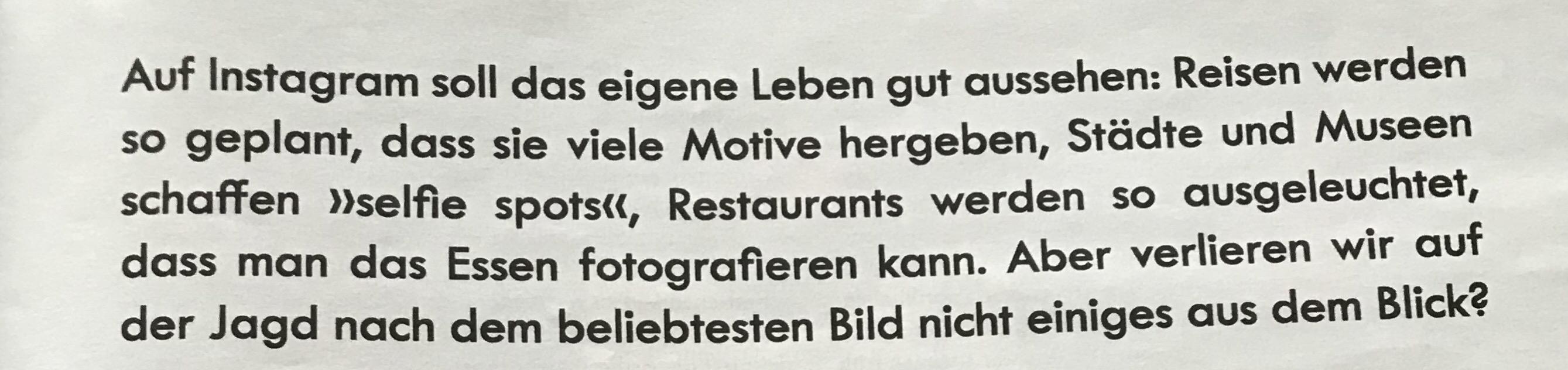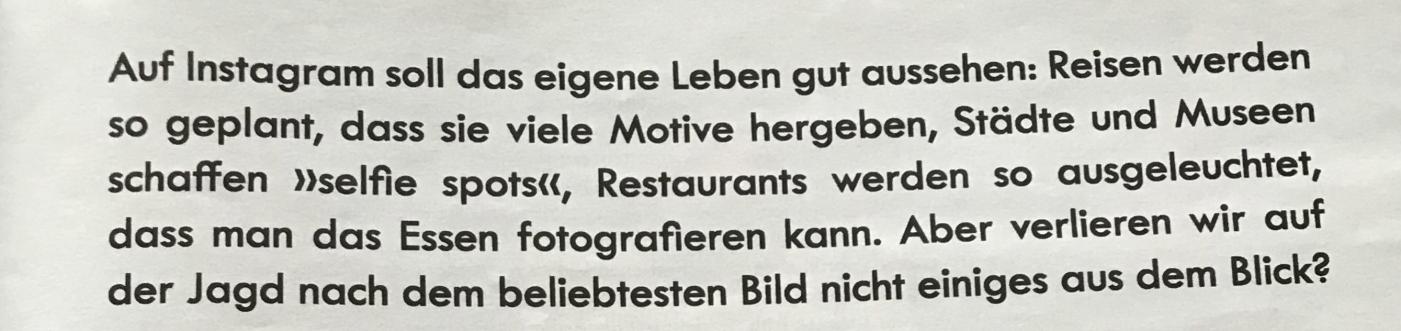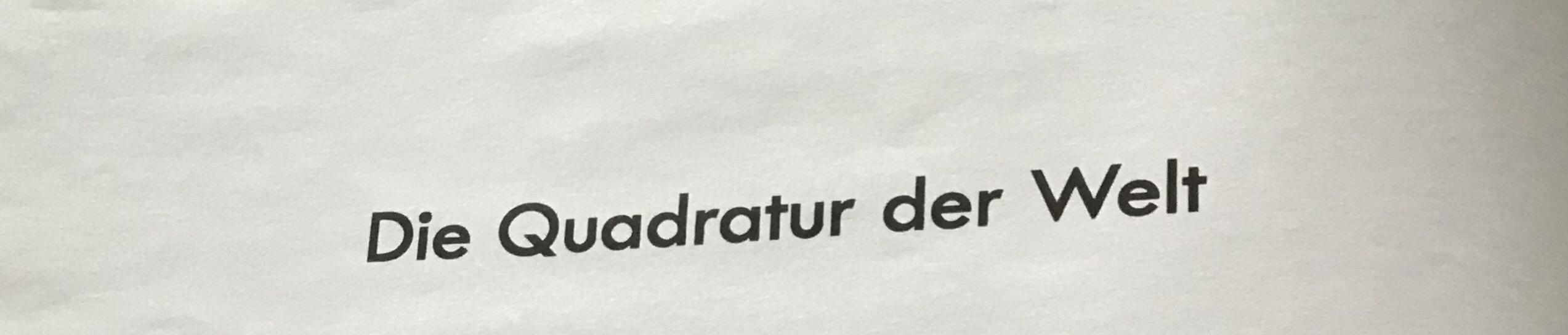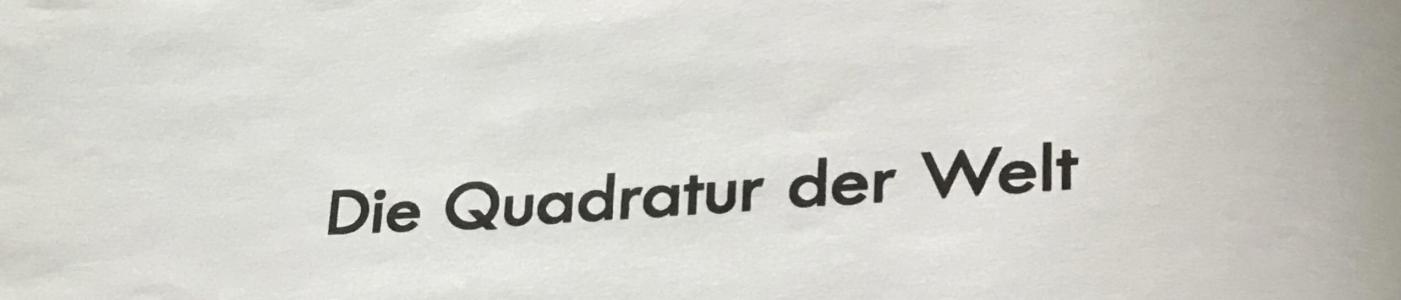
Artikel im ZEIT magazin - Schriftart?
Die Anführungszeichen sind aus einem größeren Schriftgrad.
Die Ligaturen passen ebenfalls nicht zur Futura.
Meine Bleisatzzeitkinderbücher (zu deren Entstehungszeit Futura anscheinend 1. Wahl für Kinderbücher war) haben auch solche Ligaturen.
In der digitalisierten Futura, die mir zur Verfügung steht, sehen die Ligaturen eben wie in der Abb. unten aus.
Du hast recht, im Bleisatz waren die Ligaturen wie am Foto oben.
Das sind eigentlich nur Platzhalter für Ligaturen in anderen Schriften, nicht? Hier ist ja nur am ersten f in den ff-Ligaturen der Querstrich verkürzt worden. Mit Futura-Ligaturen nach Renner hat das nichts zu tun. Die echten Verbindungen in der Futura finde ich recht schön, auch wenn »ft« unnatürlich ist und am besten gar nicht oder nur in kürzesten Texten verwendet werden sollte.
Serifenlose in Kinderbüchern finde ich an sich immer falsch, weil nicht typografisch, sondern irrig-pädagogisch gedacht, eher lesehinderlich, weil es gegen die Konventionen der Vielleser geht, die naturgemäß die bequemste Schrift bekommen (immer nahe an der Renaissance-Antiqua), und weil sich Buchstaben wir b,d,p,q oder n/u annähernd spiegeln, während sie in Serifenschriften eigene Formen haben. Aber das ist wieder eine ganz andere Diskussion. Oft ist das Kinderbuch auch falsch proportioniert. Große Bücher für kleine Hände, große Buchstaben für scharfe Augen. Dadurch werden Wortbilder eher aufgelöst als hergestellt. Eigentlich sollte das Kinderbuch dem Kind angepaßt sein und ihm funktional schmeicheln. Aber als älterer Patenonkel sind mir manche Bilderbücher (da ist die große Größe ja richtig wegen der Bildkunst) mit ihren großen Schriften wieder recht, weil ich sie ohne Lesebrille vortragen kann.
Richtig. Zum Lesen lernen und überhaupt für sehr junge Leser ist die Futura schlecht geeignet, nach meinen Erfahrungen vor allem wegen des einstöckigen a, das mit seinen geradezu winzigen Schwänzchen einem o zu sehr ähnelt. Oft sind solche winzigen »Zacken« ja Serifen und eben nicht bedeutungsunterscheidend. Aber dann unterscheiden sich ausgerechnet zwei Vokale nur dadurch!?
Aber viele (gar die meisten?) Kinderbücher werden ja von Erwachsenen (und darunter dann auch vielen Großeltern) vorgelesen. Da passt Futura (in groß) doch.
Nehme nicht an, dass diese Ligaturen als Platzhalter für andere Schriften vorgesehen sind.
So sehen die Ligaturen der digitalisierten Futura aus.
Es gibt ja Futura-Schnitte verschiedener Herausgeber, so wird es wahrscheinlich auch die Ligaturen in der Bleisatzvariante geben.
Ich wäre da für einen strengeren Respekt vor der Urheberschaft. Wenn man heute Futura-Ligatur sagt, weiß man nicht mehr, was gemeint ist. Unter »Interpretation» wird alles mögliche verstanden. Bei einer Garamond ist das etwas anderes. Deren Geschichte ist ohnehin unklar, und sie wurde immer interpretiert und angepaßt. Bei jüngeren Schriften wie der Futura, deren Urform klar dasteht, verstehe ich nicht, warum man den Namen verwendet, wenn man etwas anderes daraus macht, und sei es eben in Teilen. Es wurde ja auch an Proportionen herumgezupft.
Und eine Schrift für den Buchdruck hat in diesem Verfahren ohnehin eine andere Form, die Linearität der Linien war eher eine gedachte als eine sichtbare. Eine Futura im Offset ist schon eine leblose, zumindest kühle Kreatur, verglichen mit einer bleiernen Futura im Buchdruck, die durch den physischen Druck auf die Bleiletter ihre strenge Geradlinigkeit einbüßt. Wie schön sind die Bücher von Renner, die er in Futura setzen und vom Bleisatz drucken ließ. Splendid gesetzt und mit dem Charme des Buchdrucks. Bei all dem Interpretieren ist noch nie jemand auf die Idee verfallen, einmal das alte Druckbild nachzuahmen durch leichte Spreizungen und Biegungen in den geraden Linien bei kleinen Schriftgraden. Vielleicht ist das auch wieder Kitsch, weil doch nur Imitat. Aber Serifenlose waren in den Anfängen etwas anderes als heute. Aber das ist schon wieder ein anderes Thema und ein weites Feld.